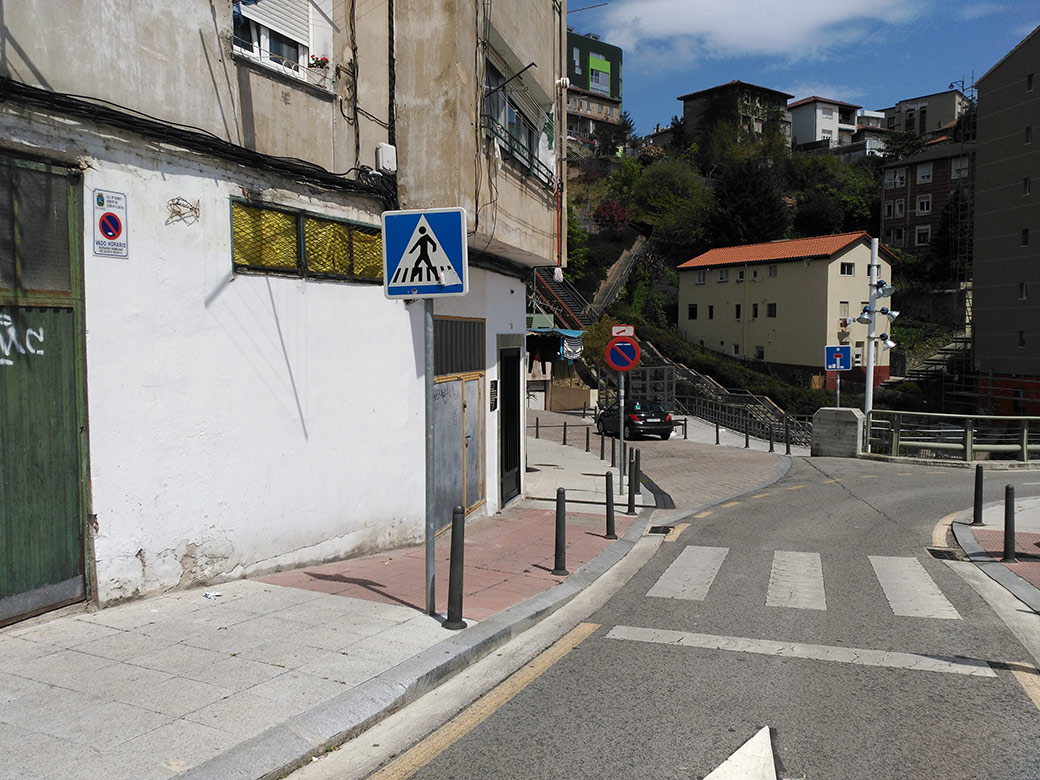
Un rótulo pequeño que puede pasar desapercibido
Está en la calle San Sebastián, cerca del funicular que sube desde el Río de la Pila y cerca de nuevo microespacio que se ha hecho en una plaza. Lo cierto que esta pequeña joya pudo ser un elemento de una pescadería adyacente, quizás un indicador. En un tamaño no superior a 30 cm, tiene una tipografía script integrada en la silueta de un pez, totalmente hecho a mano. Una rareza que perdura en una pared al paso del tiempo, y que seguro pasa desapercibido si no eres del barrio. Aquí tenéis su ubicación, a ver si le encontráis 😉